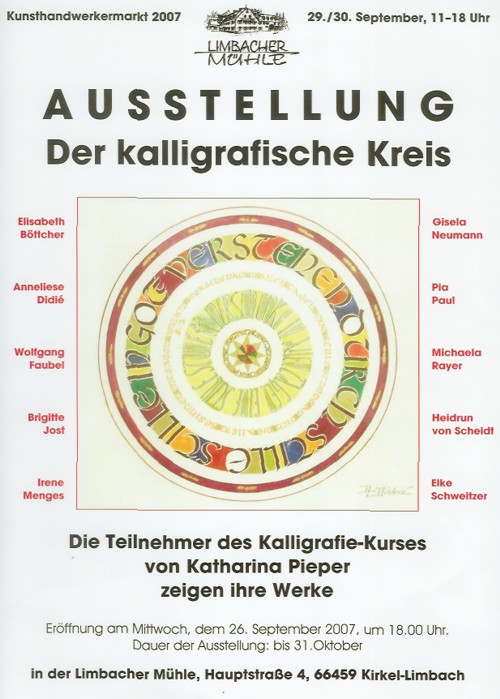
"Der Kalligrafische Kreis" ist ab 19. April im Kulturzentrum Vinningen/Pfalz zu sehen.
Die Vernissage
wird heute rund! Die Teilnehmer-Ausstellung "Der kalligrafische Kreis"
Der Kreis als universelles Thema symbolisiert wie kein anderes Motiv Einheit, Geschlossenheit, Vollkommenheit. Was sehen wir hier an den Wänden der Mühle? Ist es die Schrift, die wir als erstes wahrnehmen? Nein, es ist das Bild, das Bild des Kreises, der mittels Schrift entstanden ist. Die Schrift als Träger und Übermittler von Text und Inhalt, die Schrift in kalligrafischer Ausprägung, verschiedene Schriften wie Humanistische Kursive, Unziale, Fraktur und diverse modifizierte, personalisierte Formen der Kursiven. Hier sind wir beim Thema: was ist eigentlich Kalligrafie? Im Zeitalter des Bildschirms und der Massenmedien werden wir überflutet von hunderten, tausenden von Schriften. Schriften aus der Konserve, die irgendwann einmal von einem (mehr oder weniger hoch qualifizierten) Schriftdesigner gestaltet wurden. Schriften, die dem Transport eines Inhaltes dienen, der Kommunikation. Schriften, die heute wie kein anderes Kommunikationsmittel verunstaltet werden. Dies alles hat nichts mit Kalligrafie zu tun. Kalligrafie ist die Kunst des ausdrucksvollen Schreibens, die stille Kunst, eine Feder zu führen, die Kunst, Inhalten eine Form zu geben, der Weg, durch das verinnerlichte Schreiben zu sich selbst zu finden, Kalligrafie ist Meditation, Konzentration, Kontemplation. Kalligrafie ist aber auch lebendige Geschichte, Kulturgeschichte. Denn jede Schriftform ist in ihrer Zeit entstanden, und heute geht es darum, unseren Buchstaben neue, zeitgenössische Formen zu geben. Schrift kommt vom Schreiben, auch wenn dies Schriftanwender unserer Tage mehr und mehr leugnen wollen. Kallos Graphein, wie sich das Wort Kalligrafie ursprünglich aus dem Griechischen ableitet, "Schön Schreiben", aber auch richtig und fehlerlos. So wie Typografie wörtlich bedeutet: mit Typen, also Lettern, Buchstaben, schreiben. Fotografie bedeutet zum Beispiel dem Ursprung des Wortes nach "mit Licht schreiben". Licht finden wir hier in vielen Werken ebenso: das Licht im leeren Raum, das Licht in der unbeschriebenen Fläche, dem Raum zwischen den Buchstaben. Ohne dieses Licht wäre der Buchstabe kein Buchstabe. Erst diese "Gegenform" macht die Form zur Form. Ihr als Kursteilnehmer wisst, dass der Weg zu schönen Lettern, zu einem gelungenen Schriftstück, langwierig ist. Ergebnisse können nicht nach kurzer Zeit oder gar einem Wochenende erzielt werden. Es ist schon viel Übung und Fleiß notwendig, bis die Form der Buchstaben gelungen ist, der Text in der Fläche sitzt oder man die vielfältigen Möglichkeiten der Federführung, der Papierqualitäten oder der diversen Schreibflüssigkeiten kennt. Was lange währt, wird heute rund. Auch für mich wird genau am heutigen Tage etwas rund, und zwar begann ich vor exakt 25 Jahren, am 26. September 1982, mein Studium an der Fachhochschule Wiesbaden u.v.a. bei Prof. Werner Schneider. Ohne ihn und seinen Enthusiasmus, seine Ermunterungen, sein enormes Fachwissen und sein Verständnis von hoher Qualität wäre ich nicht Kalligrafin geworden und wir alle heute nicht hier versammelt. "Qualität kommt von Qual", eines seiner Zitate, die meisten von Euch hier kennen diesen Ausspruch. Oder "man soll sein Urteil nicht am Mittelmaß bilden, sondern nur am Allervorzüglichsten" hörte ich als Studentin immer wieder. In dieser Ausstellung ist, wie ich finde, eine wunderbare Synthese gelungen: die Vereinigung von Schrift und Bild, von Farbe und Form, von Text und Illustration, von Ausdruck und Inhalt. In der Einheit der Formgestalt des Kreises wurde unsere gemeinsame Arbeit zu einer runden Sache. Mit viel Enthusiasmus und Freude am Schaffen, viel Spaß, aber auch konzentrierter Arbeit ist hier eine harmonische Ausstellung gelungen, die sich sehen lassen kann. Ich wünsche Ihnen und uns allen einen schönen Abend, Freude am Betrachten der "Kreisbilder" und: kommen Sie nicht ins Rotieren! Vielen Dank! ....................................................................Katharina Pieper, September 2007 |